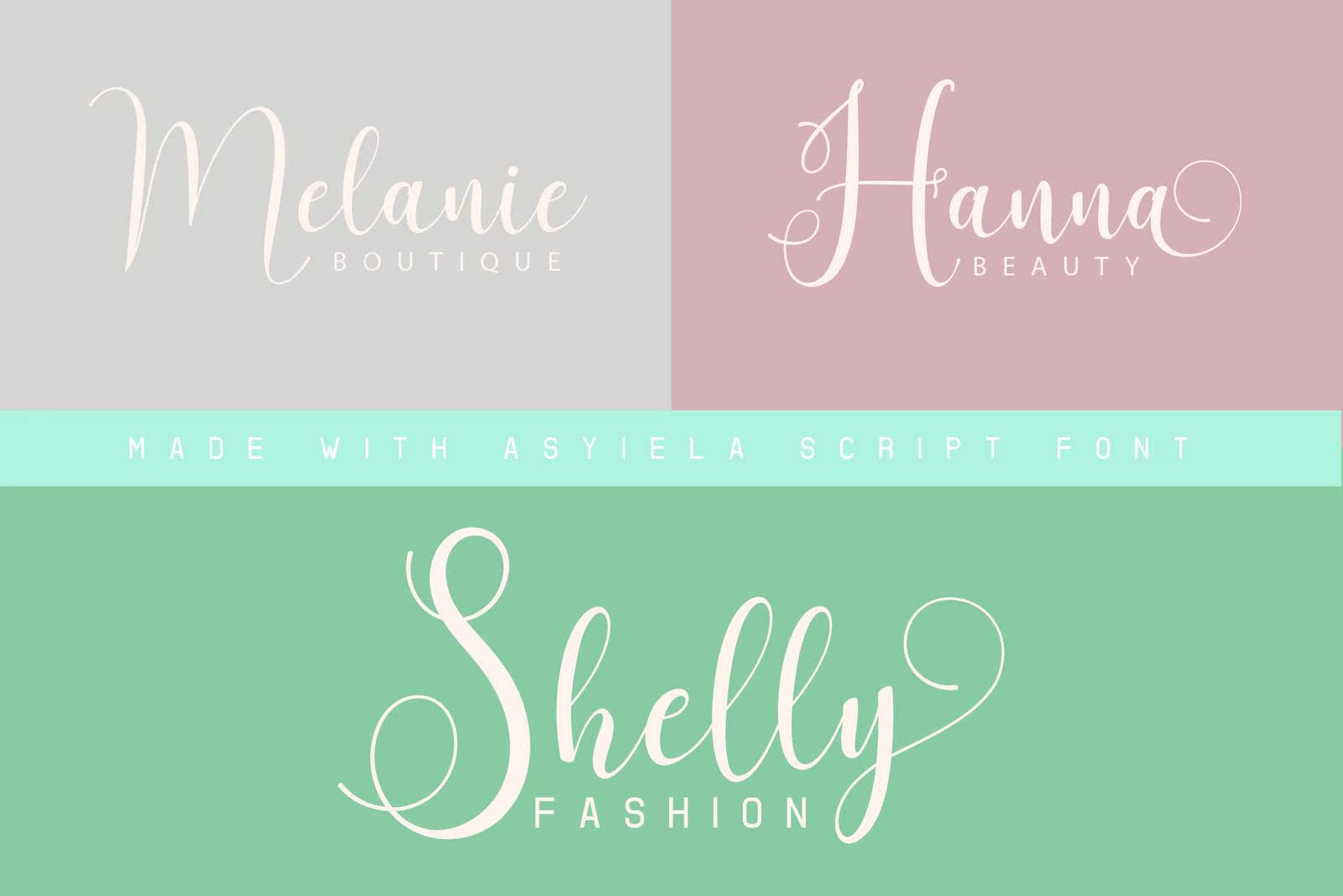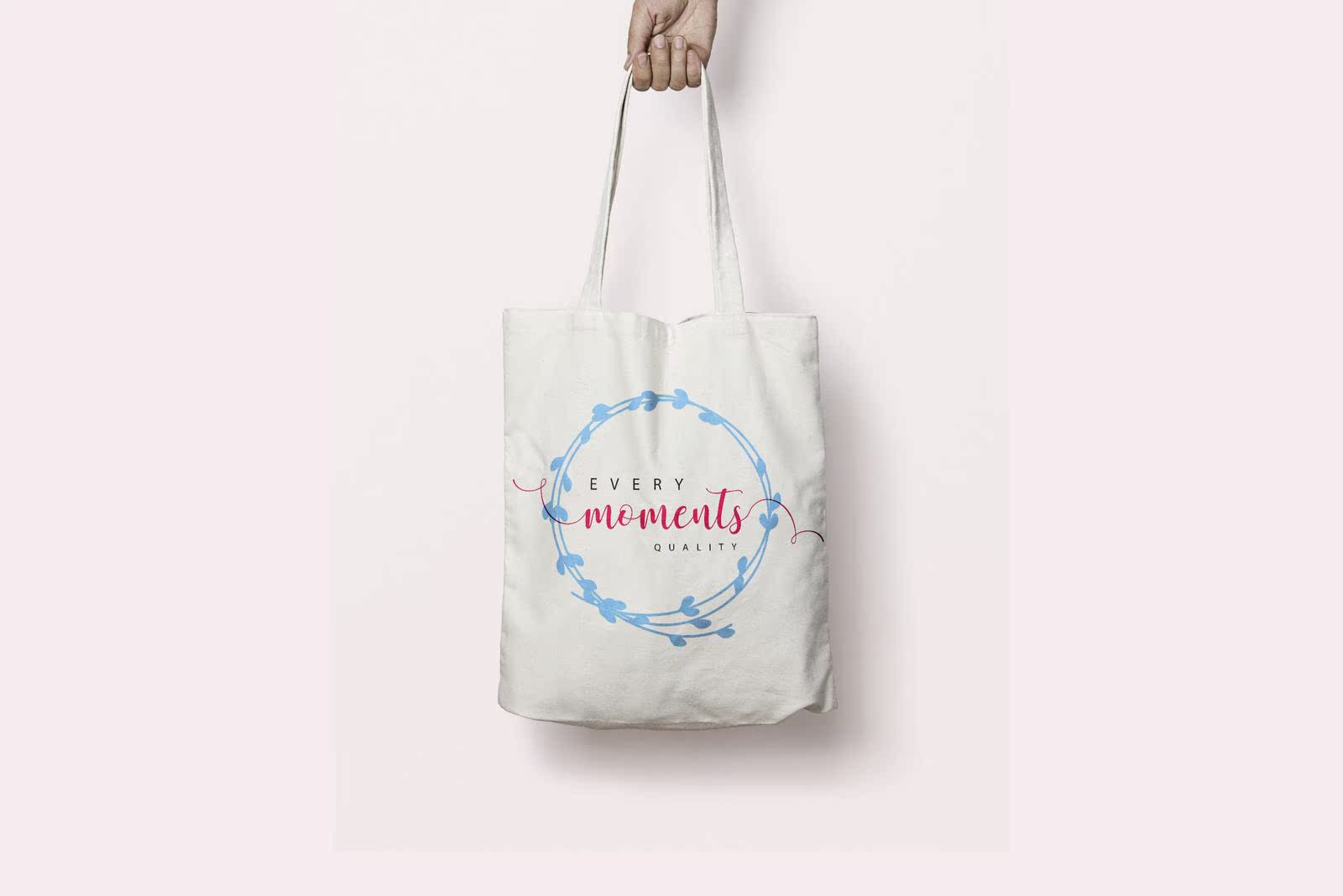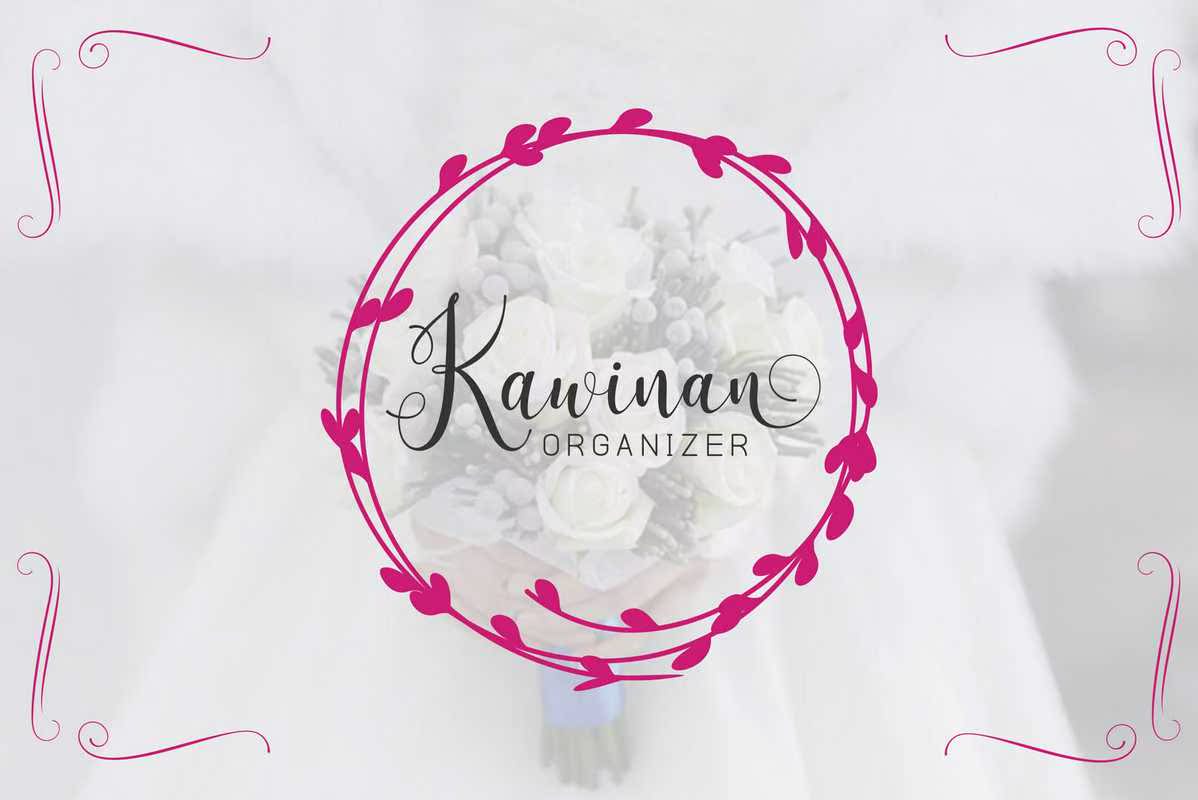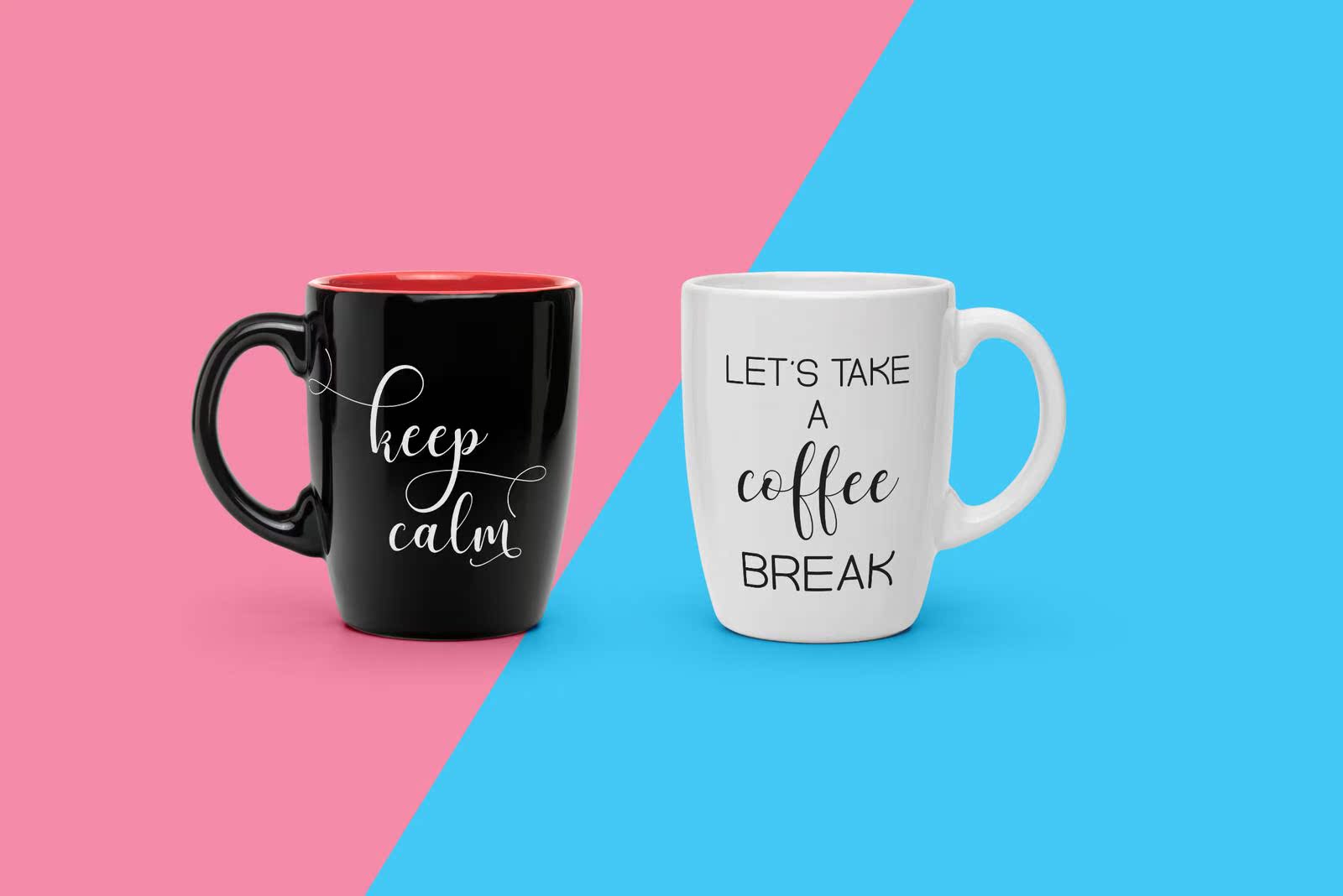
AsielaFontScript打造了爱情,这款Fonts非常适合婚礼、生日、化妆品、时尚和您想要的其他设计。AsielaFonts目前还提供带有额外花朵和名字的常规和倾斜版本。如果您现在购买这款Fonts,您将获得12美元的最高价格,并免费更新标准字体和倾斜版本以及标准字体和倾斜版本。这些更新将在下一周提供2种字体。如果此字体包完成,价格将得到调整。所有这些都是价格为2种字体的机会。同样,此字体也适用于婚礼、生日、,您想要的化妆品、时装和其他设计。AsyielaFonts目前可提供带有额外花朵和名称的常规和倾斜版本。如果您现在购买此Fonts,您将获得12美元的最高价格,并免费更新标准字体和倾斜版本以及标准字体和倾斜版本。这些更新将在下一个两周内提供,用于第二种字体。如果此字体包完成,则价格将得到调整。因此,此机会就是价格为F2字体的GET6字体。